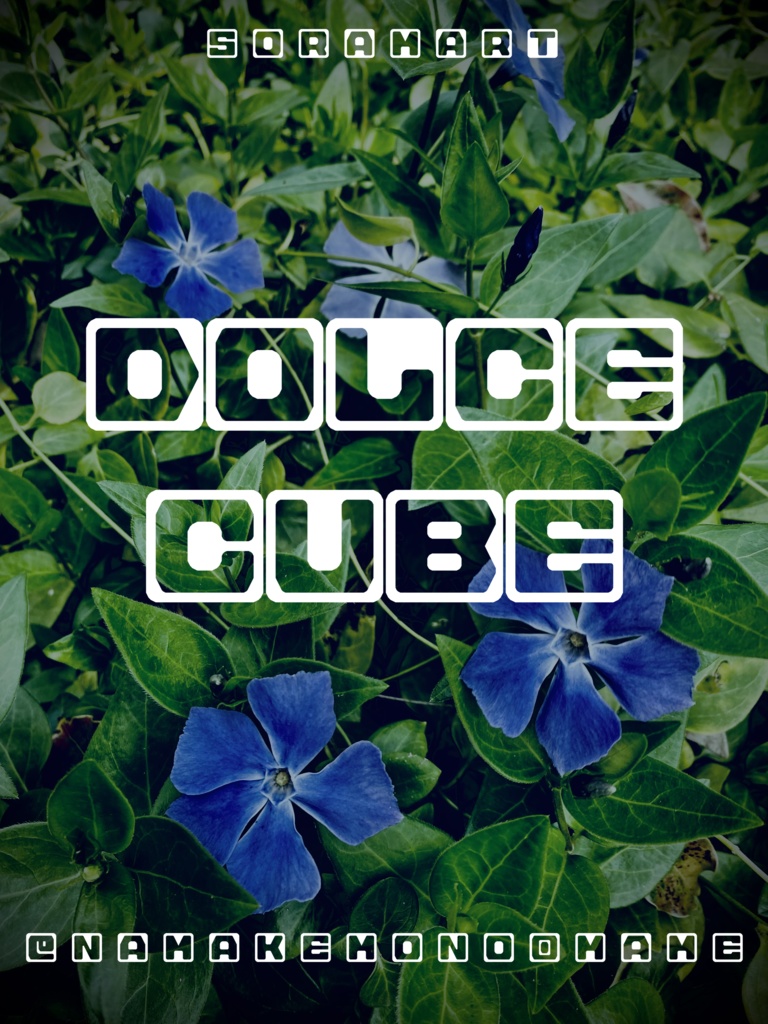
そらマートフォントデータ”Dolce Cube”Digital2,500 JPYAdd to CartBuy a GiftAbout Giftコロコロっとした、かわいらしいスタンプ風白抜きフォント "Dolce Cube" です。 「TrueTypeフォントファイル」という形式です。 ダウンロードした後、Zipファイル内のデータをインストールしてお使いください。 このフォントは商用利用可となっております。 お客様の制作・創作活動のお役に立てれば幸いです。 ※使用上の注意事項などは、添付のReadmeをお読みください。そらマートVisit FANBOX!Fontsフォントデータ”RANMMA Drive”そらマート0 JPYFontsフォントデータ”Dandy Laser Max”そらマート2,500 JPYFontsフォントデータ”Dandy Laser”そらマート2,500 JPYFontsフォントデータ”Bubblegum Beat”そらマート2,500 JPYFontsフォントデータ”Caltrop Serif LLL”そらマート2,500 JPYFontsフォントデータ”Caltrop Serif LL”そらマート2,500 JPYFontsフォントデータ”Caltrop Serif”そらマート2,500 JPYFontsフォントデータ”Tonik Crate Super Long”そらマート2,500 JPYFontsフォントデータ”Dot Eat Bug Acid”そらマート2,500 JPYFontsフォントデータ”Dot Eat Bug Mild”そらマート2,500 JPYFontsフォントデータ”Dot Eat Bug”そらマート2,500 JPYFontsフォントデータ”Solid Voltage Strike”そらマート2,500 JPYFontsフォントデータ”Solid Voltage”そらマート2,500 JPYFontsフォントデータ”Henge Edge Rock”そらマート2,500 JPYFontsフォントデータ”Henge Edge Tall”そらマート0 JPYFontsフォントデータ”Henge Edge”そらマート0 JPYFontsフォントデータ”Chisel Stroke Wide”そらマート2,500 JPYFontsフォントデータ”Chisel Stroke”そらマート2,500 JPYFontsフォントデータ”Crushed Can Serif Empty”そらマート2,500 JPYFontsフォントデータ”Crushed Can Serif Wide”そらマート2,500 JPYSee More